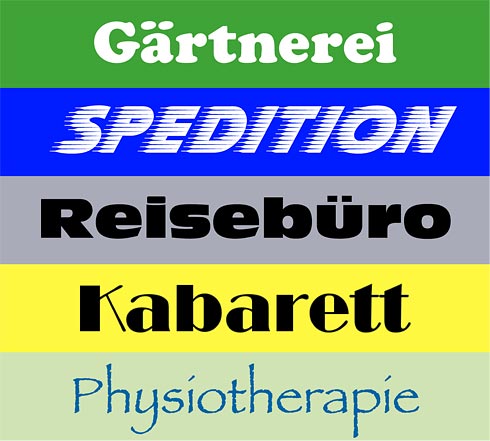
Es gibt Berufszweige, die gerne auf die immer gleiche Schrift zurückgreifen: siehe Branchenschriften, Branchenschriften (2) und Branchenschriften (3). Zur Lieblingsschrift der Gärtnereien hat sich die Cooper Black (nur 19 €) gemausert, vielleicht, weil sie zu Flower-Power-Zeiten – Ende der 60er Jahre – ihren 3 Frühling feierte. Durchaus passend für die Logistiker ist die windschnittige Slipstream, die einzige Schrift mit Rallyestreifen. Antique Olive ist die Type der »großen weiten Welt« (Peter Stuyvesant), weil sie jahrzehntelang bei der Air France im Einsatz war – von diesem Renommee können Reisebüros heute noch profitieren. Die Schrift Broadway passt ganz automatisch zu kleinen und großen Theatern, weil sie ein Kind der Musical-Meile New Yorks ist. Die zerbrechliche, biomorphe Papyrus schließlich ist der Liebling aller Wellness-Einrichtungen.
Vorschlag: Irgendeine Textur-Schrift für Bier. Selbiges gilt für Tageszeitungen.
Da gibt es natürlich viele Schriften, mir fällt spontan keine ein, aber ich finde, man könnte sich in der Richtung ruhig etwas frischeres wagen.
Dann vielleicht noch die Clarendon oder eine ähnliche Blockserifenschrift für Jeans-Labels.
Und Zapfino für Eiscafés oder Eisdielen
das mit papyrus kann ich bestätigen. und broadway ist wirklich typisch kabarett. croissant und fette fraktur sieht man auch gern bei bäcker-logos, letztere liegt auch gern beim fleischer in der auslage.
revue ist irgendwie typisch partyservice oder puff ;)
Alle möglichen Marken aus dem Bereich Mode (und deswegen auch Girlie-Zeitschriften) schmücken sich sehr gerne mit der Didot (Beispiel: http://www.vogue.de/) oder seltener auch der Bodoni, aber auch Futura scheint sehr beliebt zu sein.
Die Papyrus wird auch ständig bei Massagepraxen, Esoterikläden oder ähnlichen Einrichtungen verwendet.
Für mich ist die Cooper Black ja DIE Bäcker-Schrift. Allein hier in Weimar gibts mindestens 5.
Unsere Reisebüros hier in der Gegend (Karlsruhe) haben eher die Helvetica, die AO ist mir bisher noch nicht begegnet (ich werde aber Ausschau halten ;-) ).
Ist eigentlich irgendwo begründet, _wieso_ manche Schriften ihre Verbreitung in bestimmten Branchen haben?
Ach: Arial oder Times inkl. Wordart für Nagelstudios etc. :-)
Serpentine Bold Oblique für trendige Mode und Klamotten.
In Corel-Hochzeiten war ja alles irgendwie Avant Garde, egal ob Fahrzeug-, Fassaden- oder sonstige Beschriftung.
Was ist mit dieser zauberhaften Copperplate Gothic für PC-Läden (idealerweise mit schwarz-silbriger Einrichtung aus den 80-er Jahren) oder windige Gestaltungen aus dem Business-Bereich?
ich bilde mir ein eurostile häufig bei gallerien anzutreffen. jedoch bilde ich mir vieles ein.
die firmen- und handwerkerschrift, die mir bislang am häufigsten untergekommen ist, ist unbestreitbar die elende schriftart “Bremen” (http://new.myfonts.com/fonts/fontbureau/bremen/) und zwar schon derart häufig, dass ich schon laut überlege, fotos davon zu sammeln. ironischerweise hier in bremen. ;)
reisebusse sind übrigens entgegen aller vermutungen eine ziemlich wilde typographische spielwiese. (gefühlt 100 reisebusse dieses wochenende betrachtet, nur ein einziger war mit der “Slipstream” beschriftet.)
Rotis für alle Anwälte oder Spießer oder … ;-)
ich hab heut übrigens auch eine physiotherapie mit rotis semi sans beschriftet gesehen. aber vielleicht war die nur für architekten…
Kinderanimation, Clownerie oder Jongleure nehmen gerne mal Jokerman und auch Brush Script (je nachdem ob es eben gleich lustig-lustig aussehen soll, oder wie für und von Kindern geschrieben).
Horrorläden (Kostüm etc.) und Horrorfilme gerne Chiller oder ‘zerlaufene’ Schriftarten.
Hallo,
ist zwar schon ein Gammel-Faden, aber ich habe den erst gestern durchgearbeitet. Der Faden als solches ist für mich sehr lehrreich, da ich vor einigen Jahren (um 2006?) mal Notizen zum Thema gemacht habe. Daher habe ich einige Ergänzungen.
Speditionen/Reise:
Die Antique Olive ist idR eine Compact. Die Serpentine Bold Italic wird (oder wurde?) auch gelegentlich verwendet.
Handwerk:
Im Bauhandwerk (Dachdecker, Trockenbau) wird gelegentlich auf die Kabel/ITC-Kabel zurückgegriffen. Das scheint aber sehr neu zu sein?
Elektroinstallation/Blitzschutz:
Neuzeit Grotesk, wird häufig auf Typenschildern für rustikale Elektrik vorgefunden. Alte Elektrik aus den 1950ern und etwas später ist extrem häufig mit der Neuzeit Grotesk auf den Typenschildern. Vermutlich sogar häufiger als mit den unvermeidlichen Futura und Schriften nach DIN 1451.
Afrikanische Restaurants und Thema Afrika:
Die Neuland von Rudolf Koch (idR als Informal 011 BT), manchmal sogar eine Neuland Inline (gibts als Tribeca von Dieter Steffmann auf TypOasis frei) oder wenn`s edel wird die Tambor-Familie von Castletype(?).
Salziges Knabbergebäck (Chips, Flips):
Die ITC-Kabel ist bei einigen Herstellen dafür reserviert.
Alkohol (Whisk[e]y, Wein, Sherry …):
Neben den kalligraphischen Schriften wird die Maurice AKA Chevalier sehr gerne verwendet. Bei den Malt-Whisky in den Regalen der Kneipen sind fast die Hälfte der Etiketten in D mit der Chevalier gesetzt. Auf Weincartons findet man die Chevalier auch sehr häufig (jedoch nicht auf den Etiketten?).